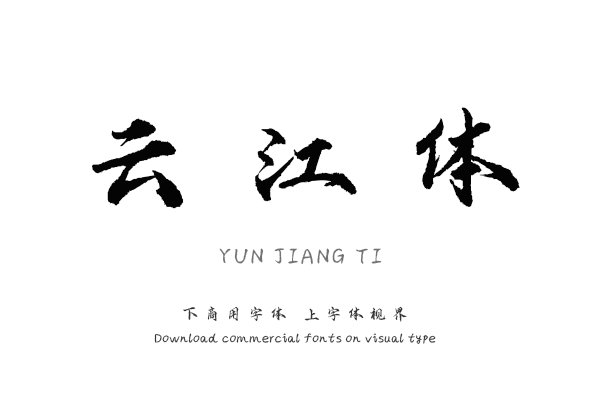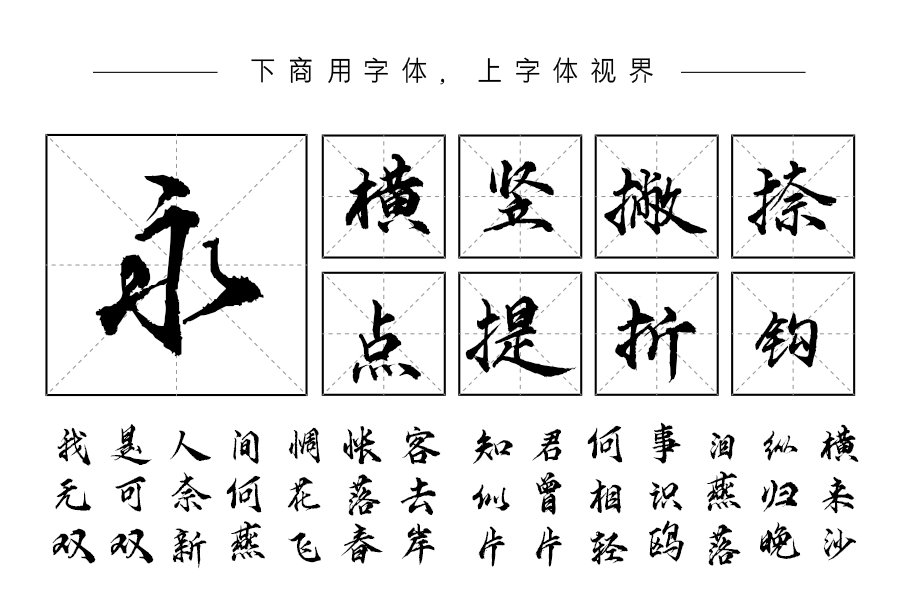
个人免费商用的书法字体-云江体
福利时间到,个人设计师们有福啦!时隔半年年之久,字体视界又发布了一款书法毛笔字体-云江体。
云江体
云江体是由陈艳艳工作室著名字体设计师何云老师耗时1年独自完成创作,由字体视界对外公开首发,供个人免费商用。
该字体笔势婉转灵动且流畅自然,具有独特的韵味,又有独特的文化魅力及笔意境界。笔画细致流畅,结构紧凑,笔意拙中带巧,不避锋芒。适用于影视、海报、封面、标题等场景中。
云江体